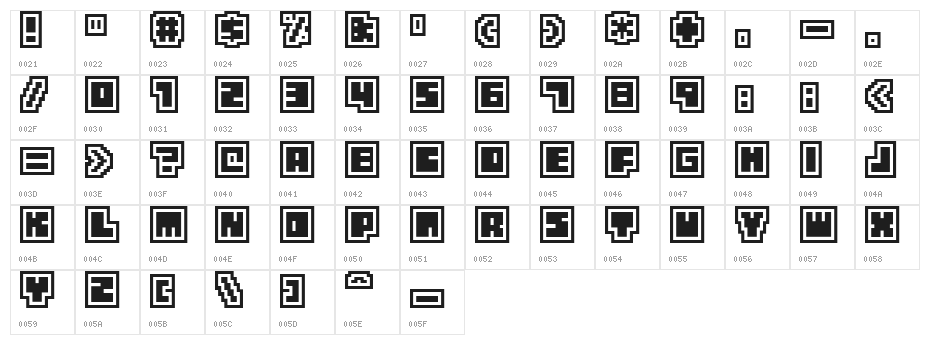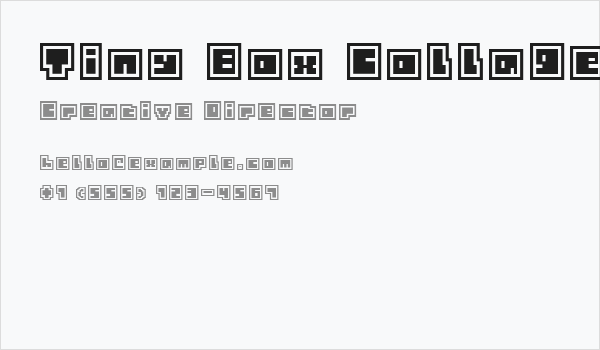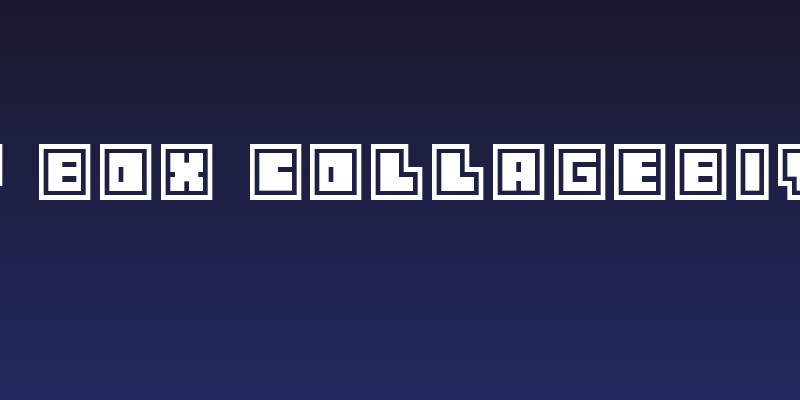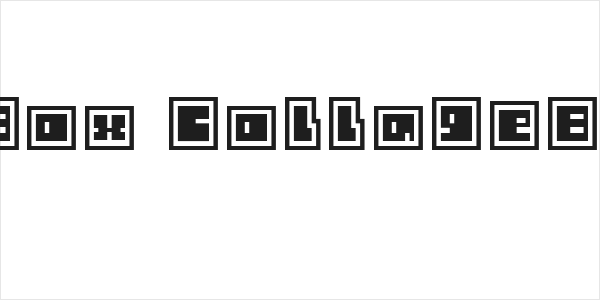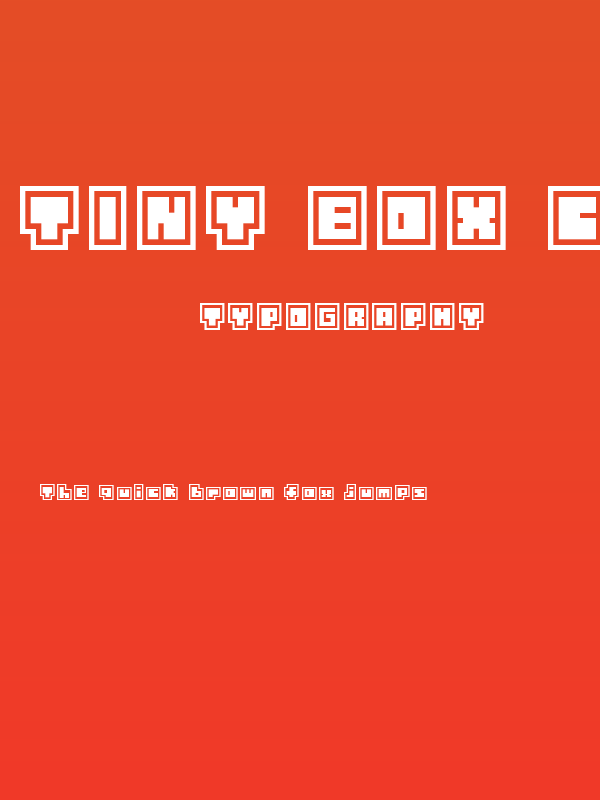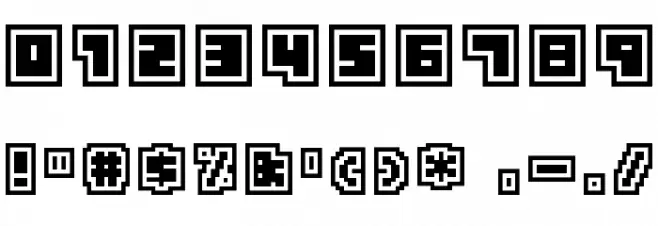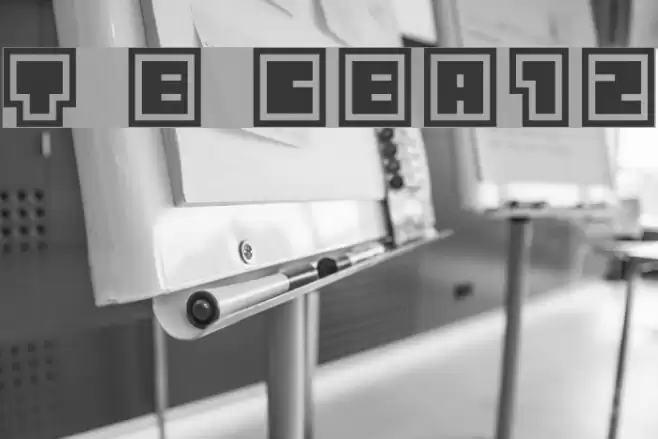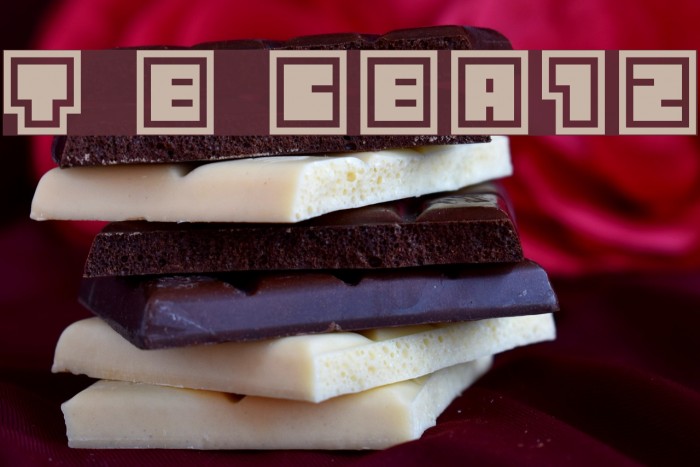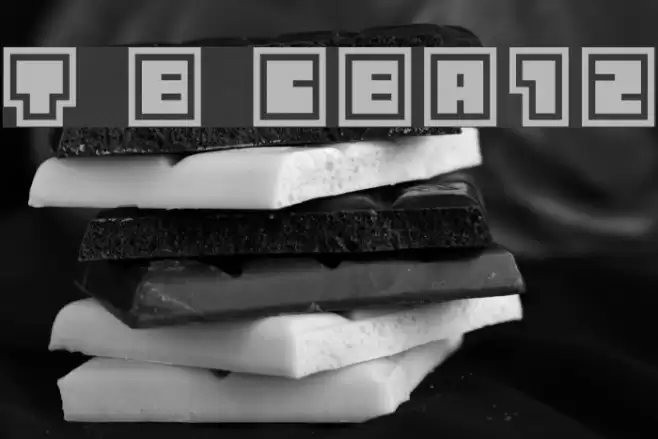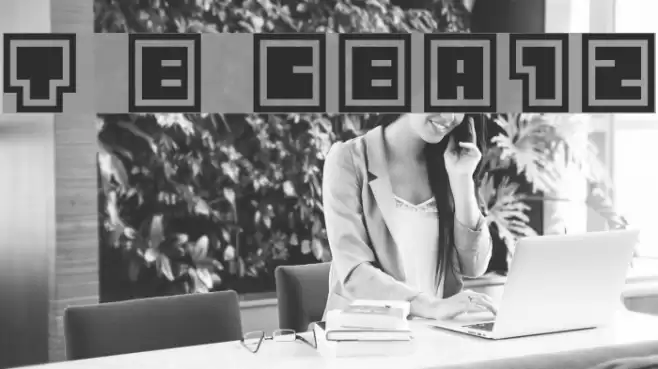
Tiny Box CollageBitA12 Font
✎ Pixel
| Gesamtstil | Retro, Digital |
| Vorgeschlagene Projekte | Ideal for video game graphics, retro-themed posters, digital art projects, and tech-inspired branding. |